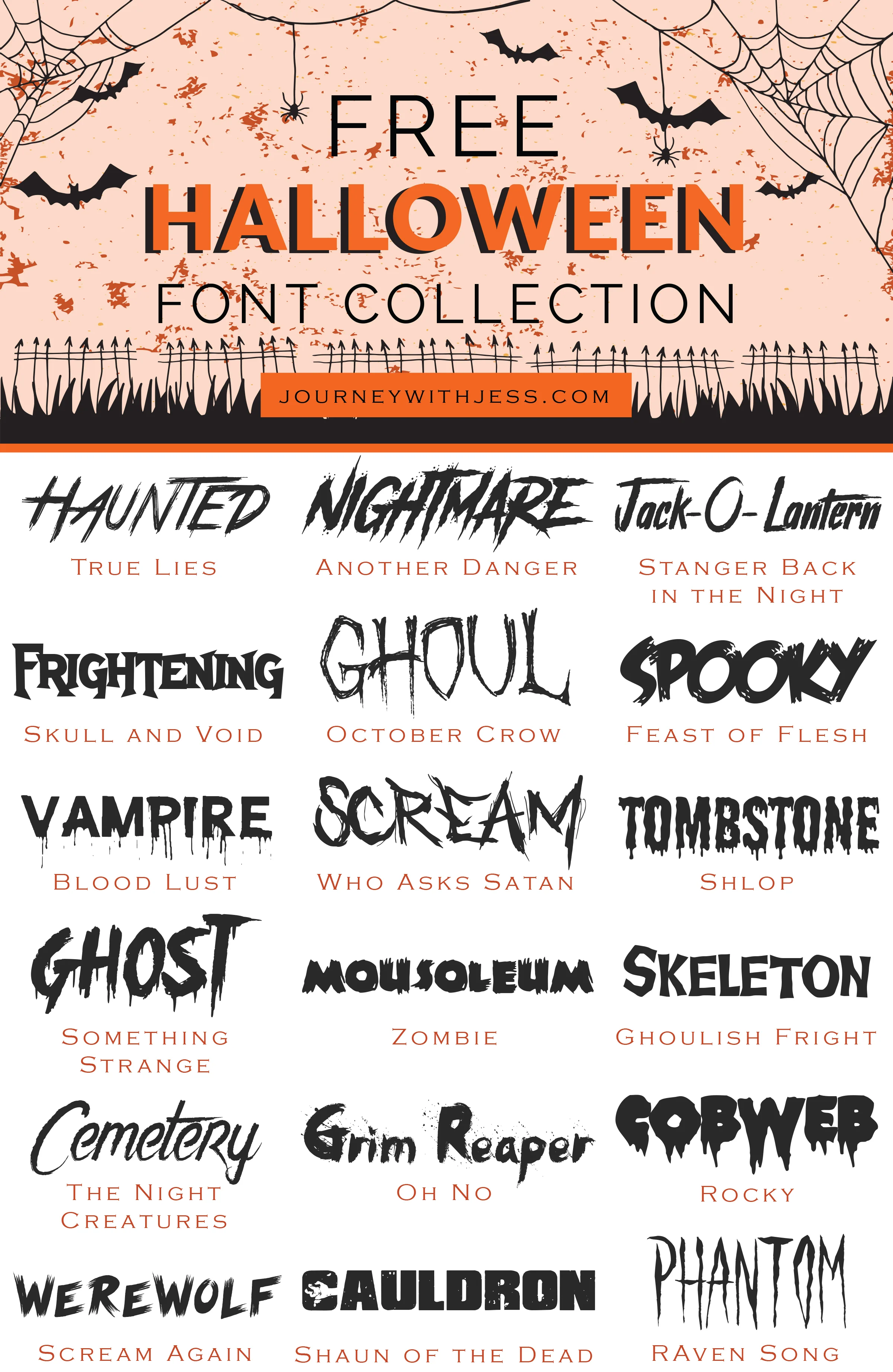
Хэллоуин шрифт: Хеллоуин Шрифты
КАК: Бесплатные Хэллоуинские шрифты с капелькой крови и страшными дингбатами
Шрифты, которые капают кровь, особенно популярны вокруг Хэллоуина. Даже в черном они выглядят так, будто они были погружены или написаны в крови. Добавьте немного графического улучшения, используя ужасные шрифты dingbat Halloween, и у вас есть идеальные шрифты для веб-страниц Хэллоуина, рекламных плакатов на Хэллоуин, а также приглашений или украшений.
Есть также несколько менее страшных шрифтов для Хэллоуина классных или маленьких детей. Шрифты, показанные здесь, доступны в виде бесплатных загрузок.
06. Винтажный Хэллоуин
Все жуткие образы, которые вам нужны в форме дингбата (Изображение предоставлено: Джим МакКоли)
Помимо стандартных шрифтов, мы также нашли несколько удобных шрифтов дингбата, которые упростят заполнение дизайн с большим количеством готовых изображений Хэллоуина. Во-первых, это Vintage Halloween от Woodcutter со стопкой полезных тыкв, летучих мышей, пауков, скелетов и многого другого, полностью векторизованных и бесплатных для личного и коммерческого использования.
07. Причудливый Хэллоуин